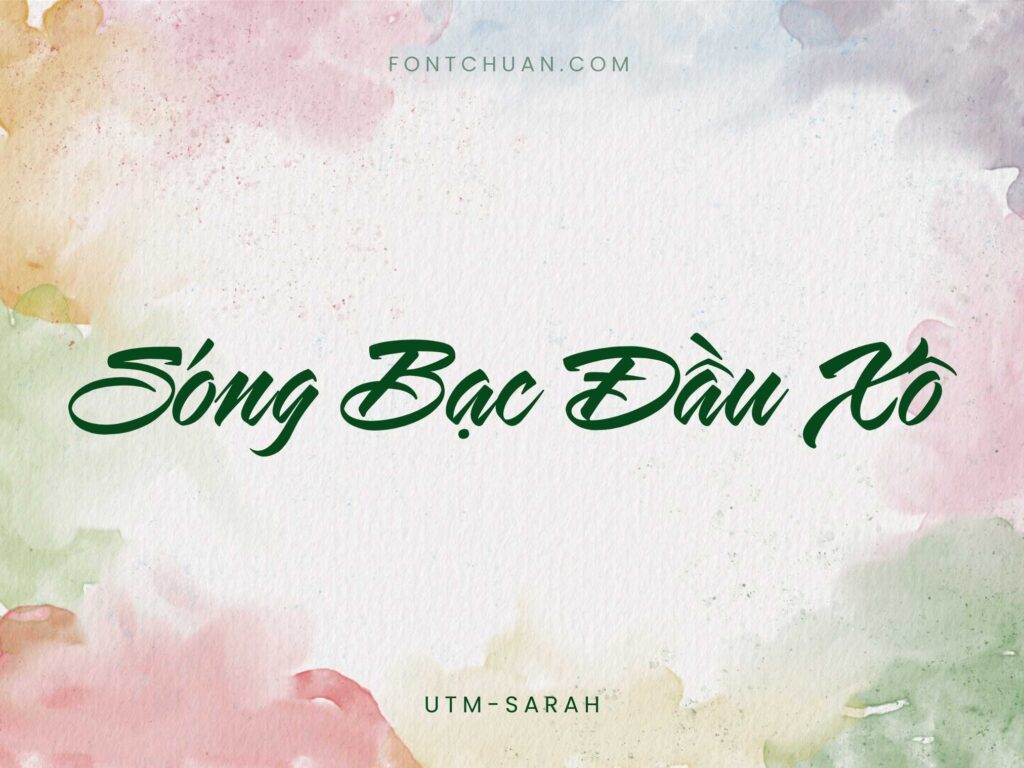
Font UTM Sarah Việt Hóa
UTM Sarah là một font chữ viết tay mang phong cách hiện đại và tinh tế, được thiết kế để tạo ra sự mềm mại và uyển chuyển trong các dự án thiết kế đồ họa. Font này có các đường nét thanh mảnh, uốn lượn tự nhiên, tạo cảm giác thân thiện và gần gũi. Font đã được Việt hóa để hỗ trợ tiếng Việt, giúp mở rộng khả năng ứng dụng trong nhiều lĩnh vực thiết kế. Thành viên của Font Chuẩn đã sưu tầm và giới thiệu font này nhằm đáp ứng nhu cầu bạn đọc, cung cấp nguồn tham khảo chất lượng và ứng dụng thực tế vào các dự án thiết kế
Với thiết kế viết tay tinh tế, UTM Sarah phù hợp cho nhiều ứng dụng như thiệp mời, thiệp chúc mừng, thiết kế logo, tiêu đề, bao bì sản phẩm và các ấn phẩm sáng tạo khác. Các ngành nghề như quảng cáo, ẩm thực, thiệp cưới và giáo dục có thể tận dụng font này để tạo nên sự độc đáo và thu hút trong các sản phẩm thiết kế